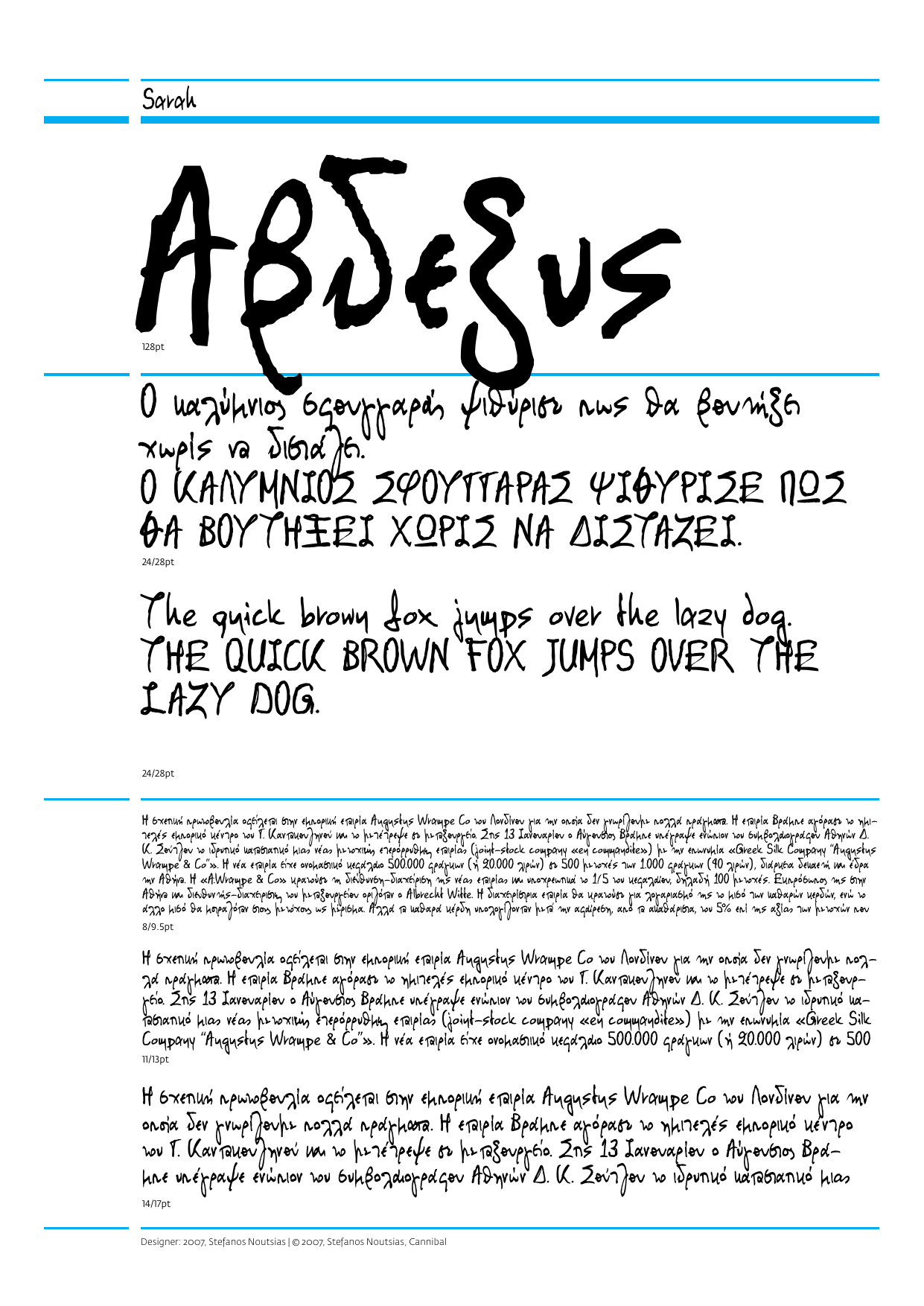
Sarah
Το χαρακτηριστικό της γραμματοσειράς Sarah που σχεδίασε ο Στέφανος Νούτσιας και επιμελήθηκε η Ειρήνη Βλάχου είναι η πληθώρα (πάνω από 50); σύνθετων (ligatures); και εναλλακτικών (alternates); χαρακτήρων που όταν συνδυαστούν κατάλληλα και τυχαία δίνουν την αίσθηση ενός χειρόγραφου κειμένου.